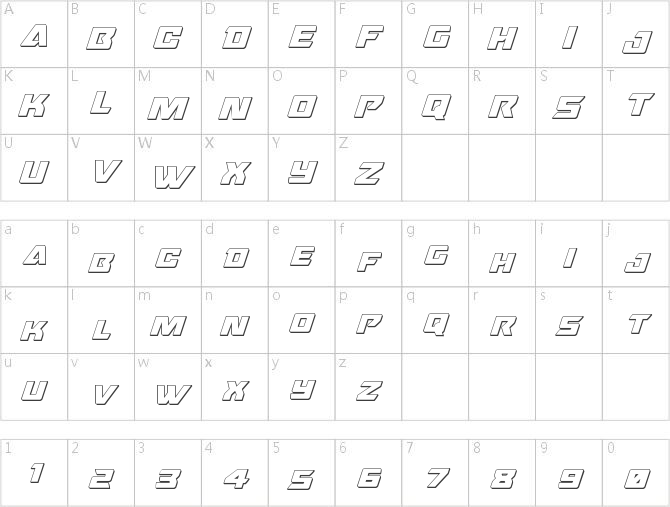
字體名稱: oceanic
oceanicdrift3dital
oceanicdrift3dital字體字庫是一款讓人賞心悅目、百看不厭的英文字體,適合各類廣告和產(chǎn)品包裝設(shè)計應用,字體大小0.06MB,格式為ttf字體,上傳用戶是浪遍塞納河的,作者/版權(quán)方為未知